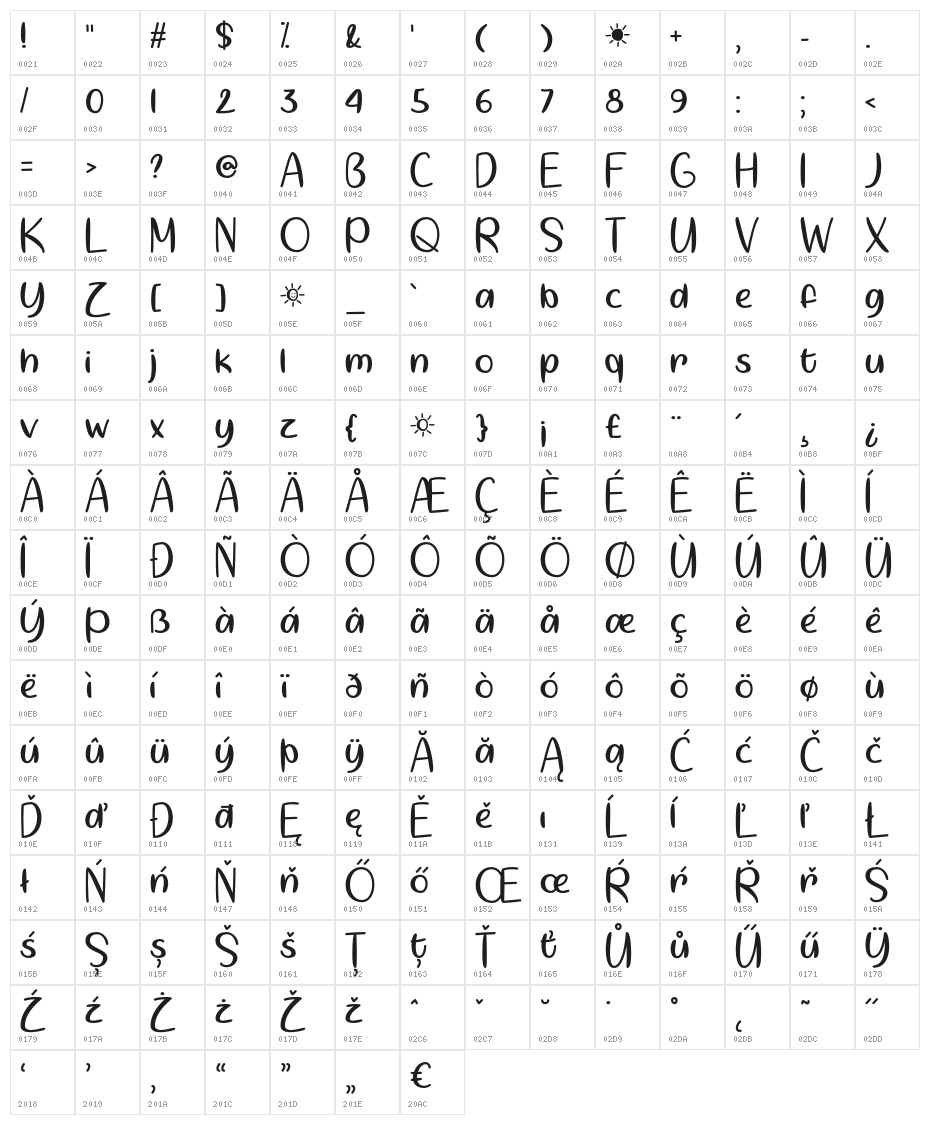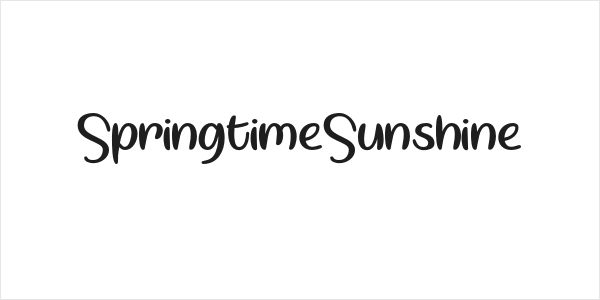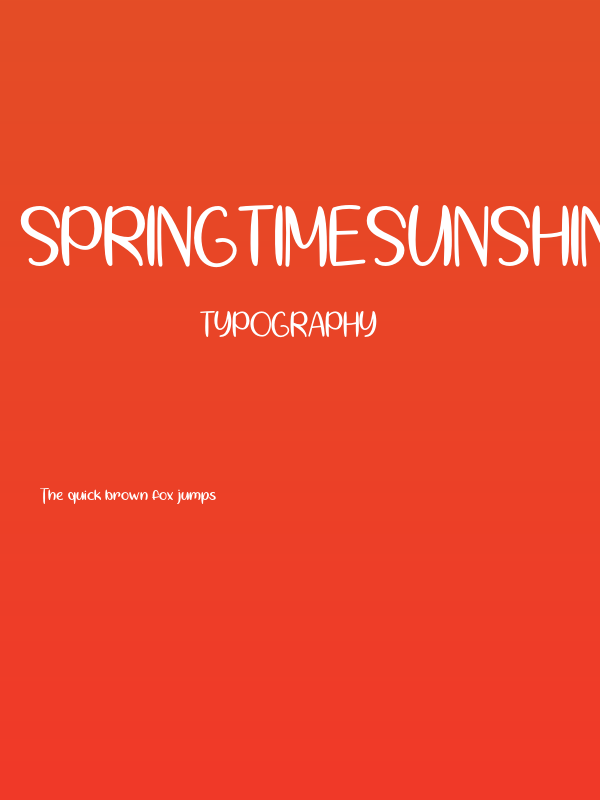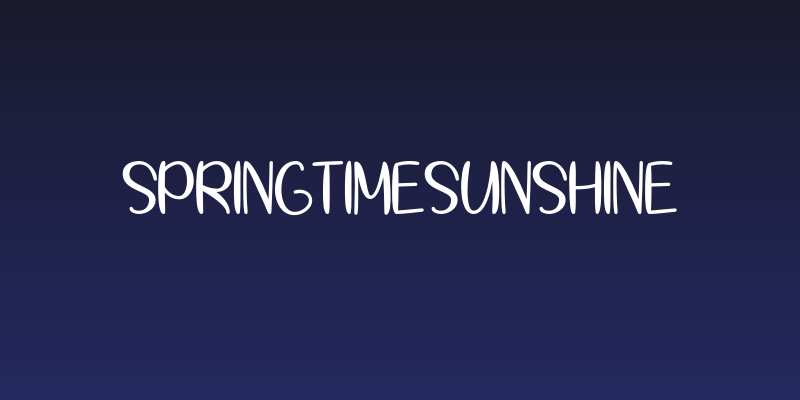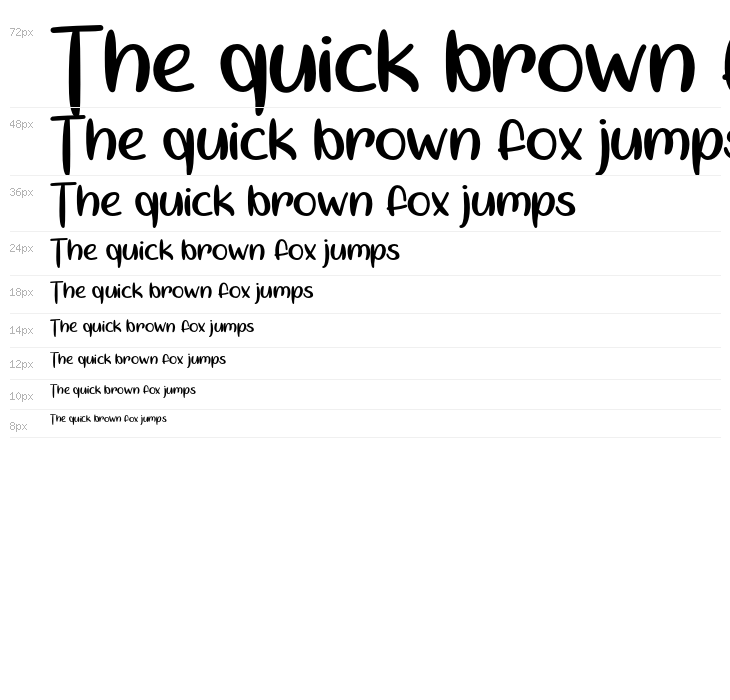
SpringtimeSunshine Font
| Estilo general | Playful |
| Caso de uso | Logos, Headlines, Informal Text |
| Proyectos propuestos | Ideal for greeting cards, children's books, playful branding, and social media graphics. |